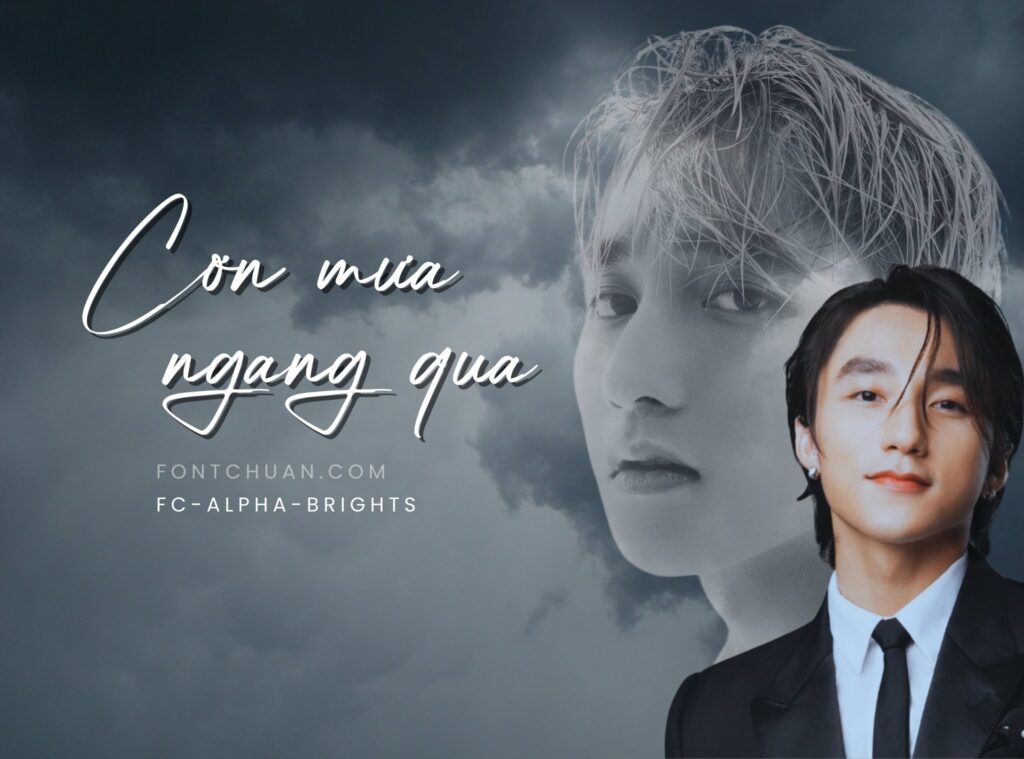
Font FC VIP Alpha Brights Việt Hóa
Alpha Brights là một Font chữ viết tay tinh tế, được thiết kế bởi Typeline Studio và phát hành vào khoảng cuối năm 2024. Với các ký tự được vẽ tay mềm mại và cân đối, font này mang lại cảm giác tự nhiên và duyên dáng.
Để hỗ trợ người dùng tiếng Việt, Font trên thị trường thường là có phí, vì vậy team Font Chuẩn đã cho ra mắt phiên bản mới Font FC VIP Alpha Brights Việt Hóa và chia sẻ miễn phí, đảm bảo hiển thị chính xác các ký tự tiếng Việt. Ngoài ra, font này còn hỗ trợ tiếng Anh và hơn 40 ngôn ngữ Latin khác, mở rộng khả năng ứng dụng trong các dự án quốc tế.
Với cấu trúc chữ mềm mại, độ dày đồng nhất và thiết kế tinh tế, Alpha Brights phù hợp cho các thiết kế yêu cầu sự thanh lịch và chuyên nghiệp. Đặc biệt, font này thích hợp cho các ngành nghề như quảng cáo, thiết kế thiệp cưới và lĩnh vực thời trang, poster MV ca nhạc, poster phim ảnh… nơi cần sự kết hợp giữa thẩm mỹ cao và chức năng truyền tải thông điệp.
Bên cạnh những ứng dụng trong thiết kế thời trang và truyền thông hiện đại, Alpha Brights còn có thể kết hợp cùng các font chữ Tết để tạo ra những mẫu typography độc đáo cho banner, bao bì sản phẩm và poster quảng cáo ngày xuân. Sự kết hợp này giúp vừa giữ được vẻ tinh tế, thanh lịch của Alpha Brights, vừa mang đến không khí tươi vui, rực rỡ đậm chất truyền thống ngày Tết.